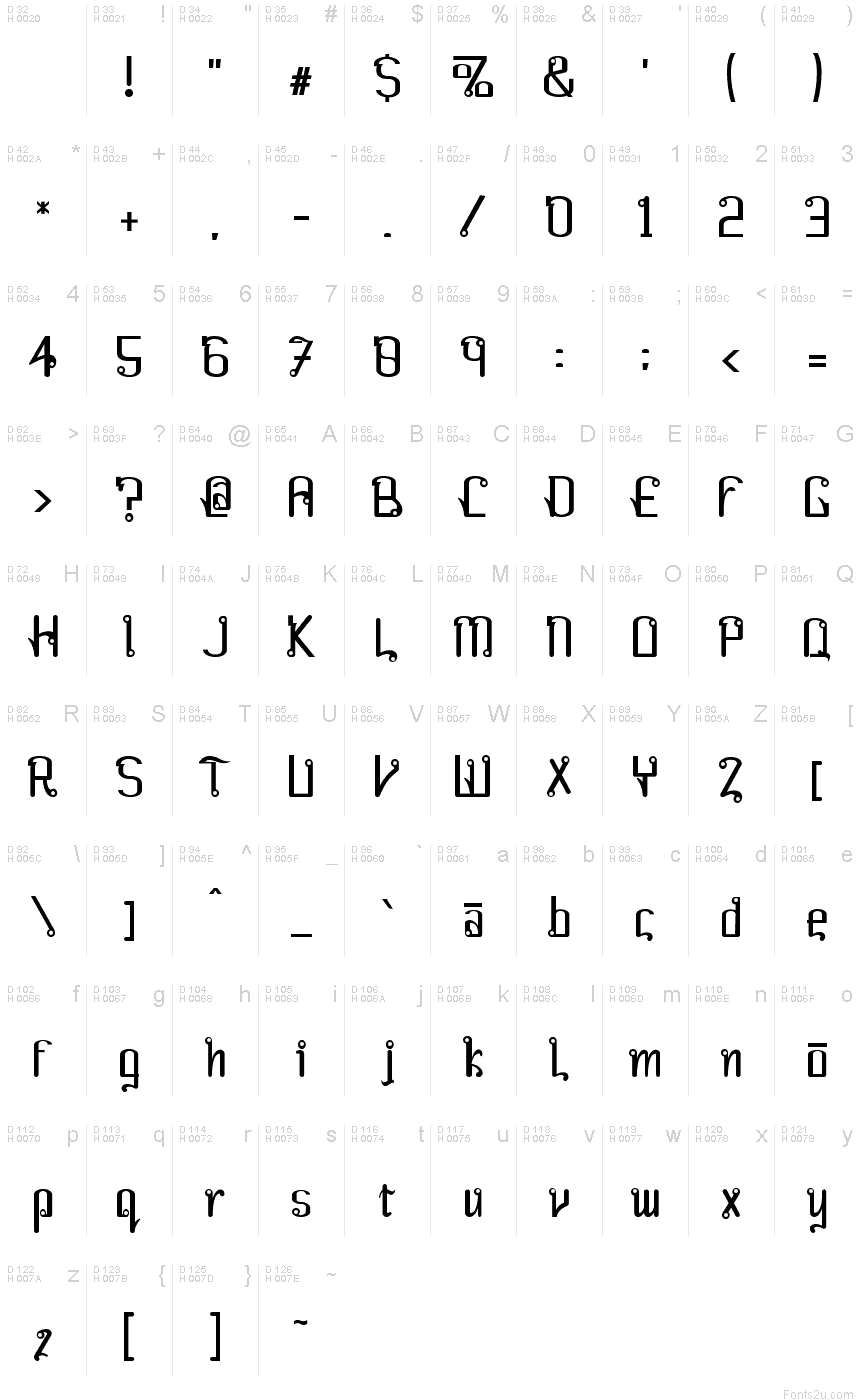
Farang
Font Farang autorstwa Michaela F Hughesa to darmowy krój pisma w tajskim stylu, który nadaje łacińskim literom wyrazisty charakter rodem z Azji Południowo-Wschodniej. Wysokie, wyprostowane formy, zaokrąglone rogi i znaki przypominające kreski unoszące się nad literami nawiązują do rytmu tajskich szyldów, a gładkie, przypominające pociągnięcia pędzla krzywizny sprawiają, że całość jest przyjazna i przystępna, unikając przy tym banałów. Efekt przypomina żywe, uliczne napisy, które można spotkać na straganach czy markizach kawiarni, przeniesione do czytelnego, cyfrowego formatu.
Używając Farang, błyskawicznie nadasz tajski lub panazjatycki klimat logo restauracji, menu, opakowaniom produktów spożywczych, plakatom podróżniczym, ulotkom wydarzeń, grafikom do mediów społecznościowych czy szyldom sklepowym. Ten darmowy font świetnie sprawdza się w większych rozmiarach, gdzie jego nawarstwione akcenty i zakrzywione kreski mogą w pełni wybrzmieć; w tekstach głównych połącz go z prostym krojem bezszeryfowym, aby zachować czytelność i wyeksponować jego dekoracyjny charakter.